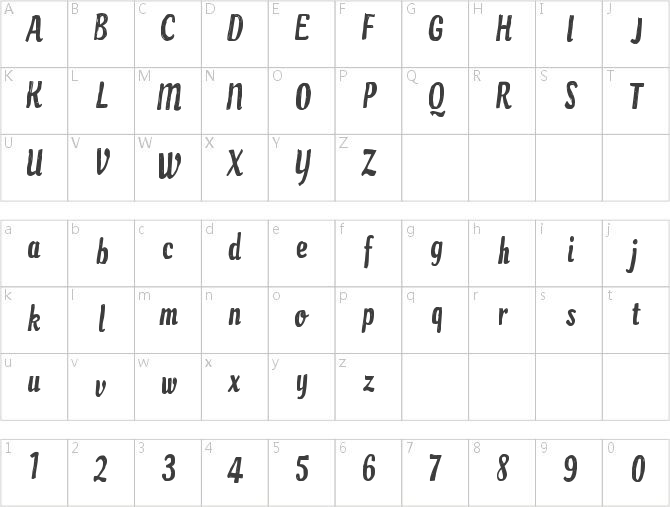
CFParadiseCity-Regular 詳情頁(yè)
CFParadiseCity-Regular字體字庫(kù)是一款讓人賞心悅目、百看不厭的英文字體,適合各類廣告和產(chǎn)品包裝設(shè)計(jì)應(yīng)用,字體大小0.05MB,格式為ttf字體,上傳用戶是手機(jī)洗相,作者/版權(quán)方為未知